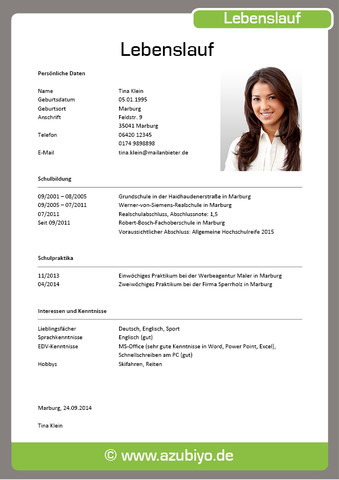
Schriftarten Fur Bewerbungen
Absolute NoGos für Schriftarten in Bewerbungen Bei Bewerbungen gibt es genug Gestaltungsspielraum, um der Bewerbungsmappe eine persönliche Note zu verleihen – wenn man einige Fettnäpfchen geschickt umgeht Für Bewerbungen haben Sie einen gewissen Gestaltungsfreiraum, auch wenn ein professionelles und seriöses Erscheinungsbild entstehen soll.
Bewerbung Schriftarten und Schriftgrößen Bei den Schriftarten einer Bewerbung sollte man also Zurückhaltung üben und sich auf eine beschränken. Für Bewerbungen sind alle diese Schriften gleichermaßen gut geeignet, weil sie eine sehr gute Lesbarkeit besitzen Auch Verdana und Garamond erfüllen diese wichtige Eigenschaft Als problematisch hingegen gelten alle Schriftarten, die zu stark von der Norm abweichen. Die einen halten Times New Roman für eine Universalwaffe, für die anderen ist sie einfach nur altmodisch und langweilig Das Gleiche ließe sich über Arial sagen, das oft in Geschäftsbriefen verwendet wird Die Meinungen über Schriftarten gehen auseinander, so viel steht fest.
Die Wahl der Schriftart für die Bewerbungsunterlagen Lesezeit 2 Minuten Auch in Bewerbungen gelten die Schriftarten "Times New Roman" und "Arial" unter MS Word mittlerweile als ziemlich abgegriffen Welche Schriftarten sich alternativ für Ihre Bewerbungsunterlagen anbieten, lesen Sie hier. Diese Schriftarten sind frei von Serifen (den kleinen Strichen an den Enden der Buchstaben) und da sie professionell und gut strukturiert wirken, kannst du sie auch für Bewerbungen bei eher konservativ eingestellten Unternehmen verwenden, um dich abzuheben Wenn es doch etwas kreativer sein darf, empfehlen sich Schriftarten wie Garamond. Fonts for Instagram This is a simple generator that you can use to make fonts for Instagram Simply put your normal text in the first box and fonts for Instagram bio/captions/etc will appear in the output box with all sorts of cool symbols.
Nicht jede Schriftart ist dazu geeignet, in der Bewerbung eingesetzt zu werden Einige der von Microsoft oder Apple angebotenen Schriftarten eignen sich eher für (Kinder) Geburtstagseinladungen als für einen professionellen Eindruck in der Bewerbungsphase. Absolute NoGos für Schriftarten in Bewerbungen Bei Bewerbungen gibt es genug Gestaltungsspielraum, um der Bewerbungsmappe eine persönliche Note zu verleihen – wenn man einige Fettnäpfchen geschickt umgeht Für Bewerbungen haben Sie einen gewissen Gestaltungsfreiraum, auch wenn ein professionelles und seriöses Erscheinungsbild entstehen soll. Nicht jede Schriftart ist dazu geeignet, in der Bewerbung eingesetzt zu werden Einige der von Microsoft oder Apple angebotenen Schriftarten eignen sich eher für (Kinder) Geburtstagseinladungen als für einen professionellen Eindruck in der Bewerbungsphase.
Diese Schriftarten sind frei von Serifen (den kleinen Strichen an den Enden der Buchstaben) und da sie professionell und gut strukturiert wirken, kannst du sie auch für Bewerbungen bei eher konservativ eingestellten Unternehmen verwenden, um dich abzuheben Wenn es doch etwas kreativer sein darf, empfehlen sich Schriftarten wie Garamond. Ich schreibe gerade an einer Bewerbung für eine Stelle, die ich unbedingt haben möchte Allerdings ist es meine erste Bewerbung und deshalb bin ich in vielen Punkten etwas unsicher Die meisten davon habe ich inzwischen. Die besten Schriftarten für eine Bewerbung Garamond, Helvetica, Georgia und Co Eine der besten Schriftarten für eine Bewerbung – Garamond Die Schriftart dürfte nicht unbedingt jeder in seinem Alltag nutzen Hier taucht sie auf, weil sie eine hervorragende Alternative zu Times New Roman ist.
Nutze niemals mehr als zwei Schriftarten Für Überschriften und Kategorien bietet sich eine serifenlose Schrift an Für den Rest eine Serifenschrift Mehr wirkt unübersichtlich und unruhig Deine Bewerbung sollte Souveränität ausstrahlen Orientiere dich bei der Auswahl der Schriftart(en) an der Branche, in der du dich bewirbst. Für Bewerbungen in den sogenannten seriösen Berufen wie Bank oder Versicherungsunternehmen ist es wichtig, einen modernen und disziplinierten Eindruck zu machen Daher eignen sich hier serifenlose, geradlinige Schriftarten Für kreative Berufe dagegen sollten Sie sich dagegen für eine Serifenschrift entscheiden. Schriftarten für Bewerbungen Diese.
Schriftgröße Bewerbung Üblicherweise werden Schriftgrößen in einem Bereich von 11 bis 13 Pt für Bewerbungen, Anschreiben sowie Lebenslauf gewählt Die genaue Schriftgröße hängt von der Schriftart ab Für ein Bewerbungsschreiben in Arial eignen sich 11 Pt, wohingegen Calibri sowie Times New Roman in 12 Pt besser wirken Das Schriftgröße Bewerbung Beispiel zeigt Abhängig von. Bezüglich der Schriftfarbe sprechen sich die Experten von besserbewerbende für das klassische Schwarz aus Optional und je nach Branche können Farbelemente verwendet werden, um Aufmerksamkeit zu erregen oder den Blick des Lesers zu steuern Zum Beispiel könnten Trennlinien in einer der Farben des Unternehmens gewählt werden. Schriftarten in der Bewerbung Welche ist die richtige?.
Wir erklären Ihnen, mit welchen Schriftarten Sie Ihre Chancen verbessernDas Beste aus der CHIP Videowelt!. Absolute NoGos für Schriftarten in Bewerbungen Bei Bewerbungen gibt es genug Gestaltungsspielraum, um der Bewerbungsmappe eine persönliche Note zu verleihen – wenn man einige Fettnäpfchen geschickt umgeht Für Bewerbungen haben Sie einen gewissen Gestaltungsfreiraum, auch wenn ein professionelles und seriöses Erscheinungsbild entstehen soll. Die gängigen Druckverfahren für Visitenkarten OffsetDruck Offset, also der Klassische Druck mit Platten, ermöglicht eine enorm hohe Auflösung Das macht sich vor allem bei der Lesbarkeit von Text bemerkbar Auch schmalere Schriftarten lassen sich im OffsetDruck gestochen scharf umsetzen.
Anregungen für eine kreative Bewerbung Fakt ist Personalverantwortliche, gerade großer Unternehmen, erhalten täglich eine Vielzahl an Bewerbungen, sodass pro Bewerbung im Durchschnitt gerade einmal ein bis zwei Minuten zum Sichten der Unterlagen bleibenBei über hundert Bewerbungen für eine Stelle wird deswegen ziemlich schnell und gnadenlos aussortiert. Die Wahl der Schriftart für die Bewerbungsunterlagen Lesezeit 2 Minuten Auch in Bewerbungen gelten die Schriftarten "Times New Roman" und "Arial" unter MS Word mittlerweile als ziemlich abgegriffen Welche Schriftarten sich alternativ für Ihre Bewerbungsunterlagen anbieten, lesen Sie hier. DIN 5008 macht Angaben zu Zeilenabständen, Hervorhebungs und Schriftarten, Schriftgrößen, Seitenrändern und weiteren Gestaltungselementen Die Vorgaben sind Empfehlungen und gerade für Bewerbungen, die sich ja auch durch Individualität vom Rest der Bewerbermasse abheben sollen, nicht in Stein gemeißelt!.